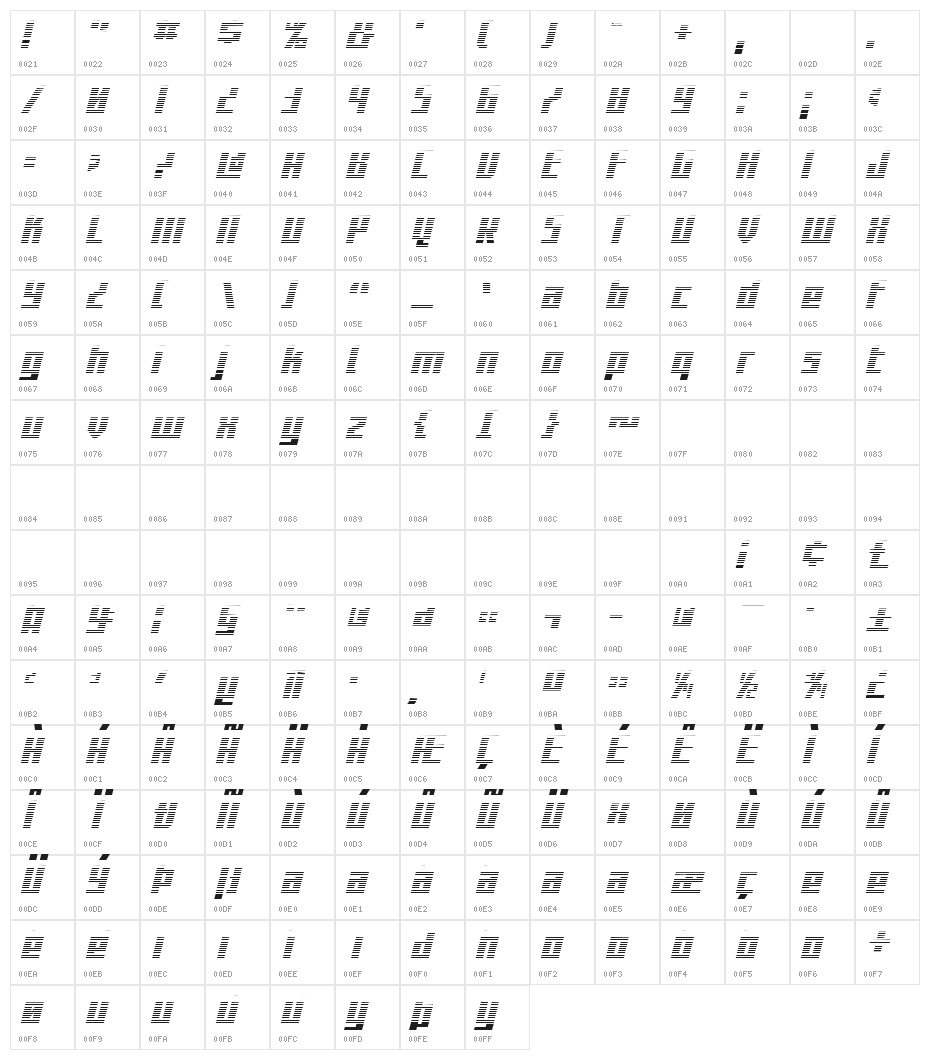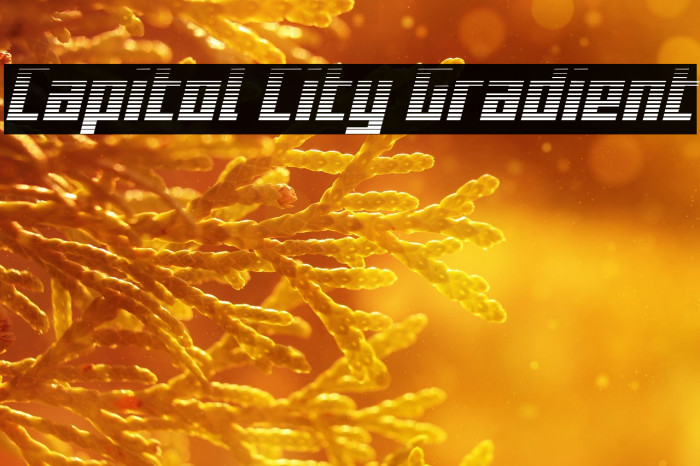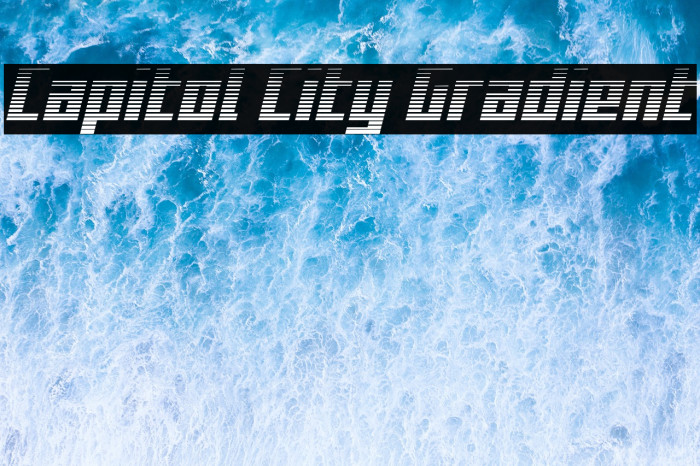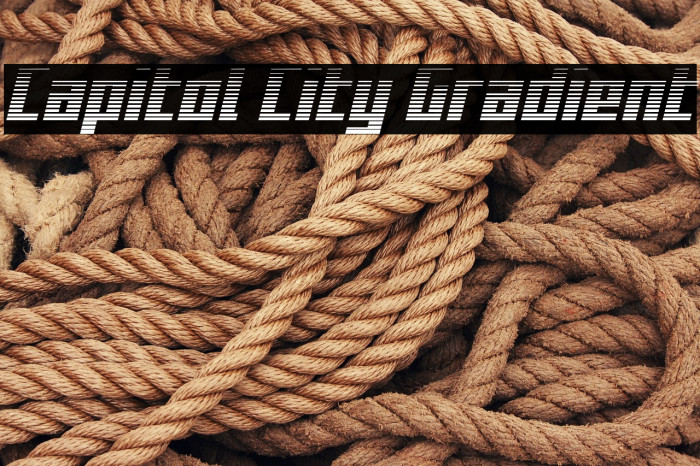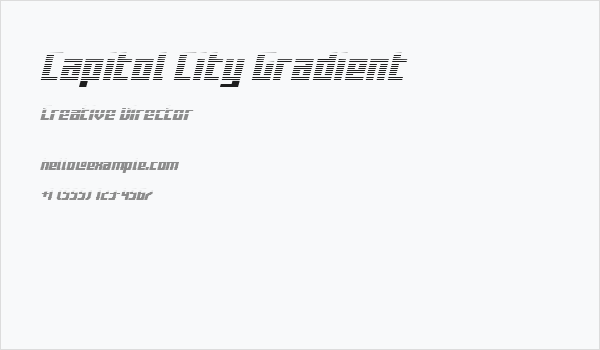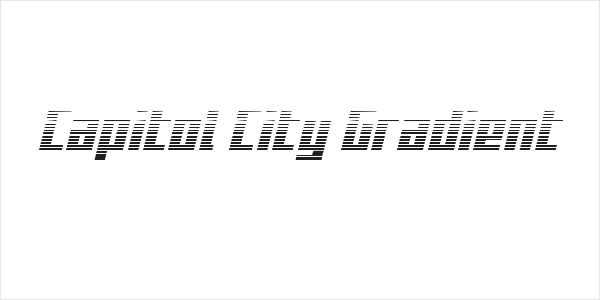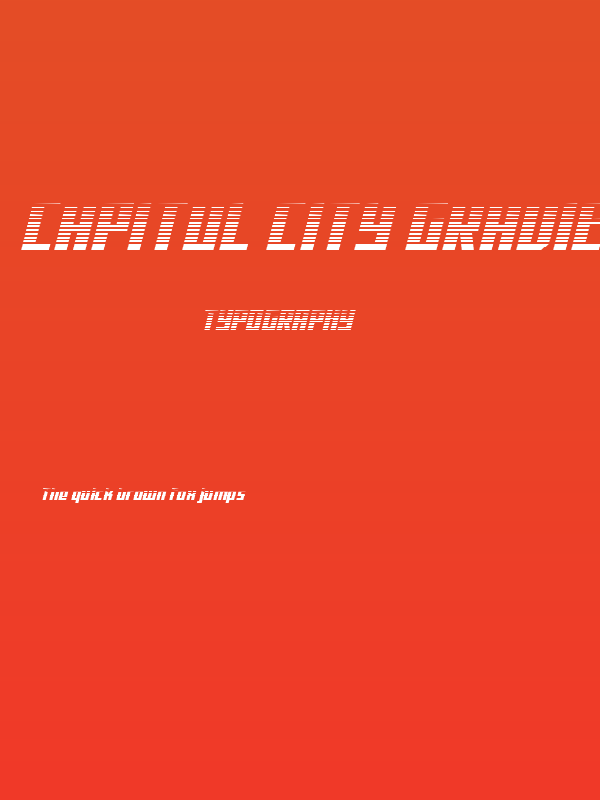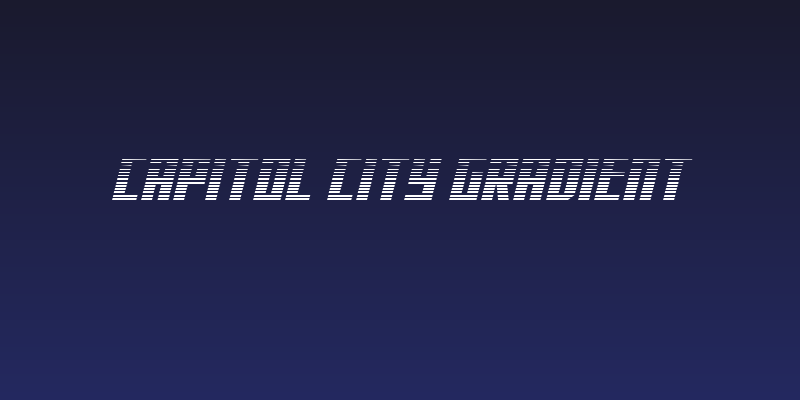
Capitol City Gradient Font
| Vorgeschlagene Projekte | Ideal for projects that require a modern and dynamic look, such as tech-related branding, futuristic posters, or video game titles. |